黄海为《少年的你》设计的海报,字体亮眼了!
由易烊千玺和周冬雨主演的电影《少年的你》
当然对于设计师来说
并不是期待这部电影演的有多好看
而是海报设计的水准高不高
嗯,如你所愿
本次的海报是黄海亲自操刀设计的
因这部电影讲的是优等生陈念和小北
在校园暴力的环境下,两个人在18岁的年纪
提前尝到了成人世界的漠然
他们一起保护少年尊严的故事
所以主海报设计上
将少年骑车的背影和周边的场景进行模糊处理
以此来体现骑车的速度刺激感
符合电影主题“少年”的概念
同时,将红黄蓝绿这四种颜色的过渡非常自然
骑车奔跑的地面,用蓝、黄、草绿这三种颜色进行呈现
且将周围的树和红墙配色融合在整体的画面当中
而与之搭配的字体设计
用泼墨书法的感觉,将“少年的你”这四个字融合一体
其中“少年”二字共用笔画,“的你”置于下方
竖线或者丿的笔画较细,有种线条流动的错觉
让这四个字体形成一个整体配合画面去呈现和延展
当然,黄海设计的海报一直都在水准上
看到各位网友的评价就知道了
据说片名字体的设计
经过黄海几个月时间的打磨
一笔一画都是设计师对电影内核的呈现
字体被应用于各种人物类型的主宣传海报上
配合画面的场景,非常具有代入感
例如下面这张正式海报的设计
这张海报设计采用了上下分割的排列形式
将“少年的你”这四字被放大置于画面的正上方
而海报男女主人公
在下雨天互相依偎淋雨的场景,沉重又温暖
同时主演的名字
被隐藏在少年的你这四个字下面
让画面统一,形成一个整体
再搭配上暖心的文案“你保护世界,我保护你”
讲真,光看到海报
就已经对电影有很大的期待了
电影海报的作用是以静态的画面表达动态的行为
就好比将画面中比较虐心的场景被提取出来
作为单独的海报画面去吸引观众了解的欲望
从而促成“购买电影票去看电影”的行为动机
这才是一个很优秀的电影海报设计
像下面这种
易烊千玺被勒住脖子痛苦的申请
和周冬雨奔溃的眼神中去感知
电影所传递出的“被保护”的含义
当然人物角色的海报设计
用男女主人公坚定的神情搭配上电影海报的字体
以满版式布局去体现画面的主体
还有像这种
人物角色的海报设计以左右分割的形式
来突出画面的主体人物角色和情绪
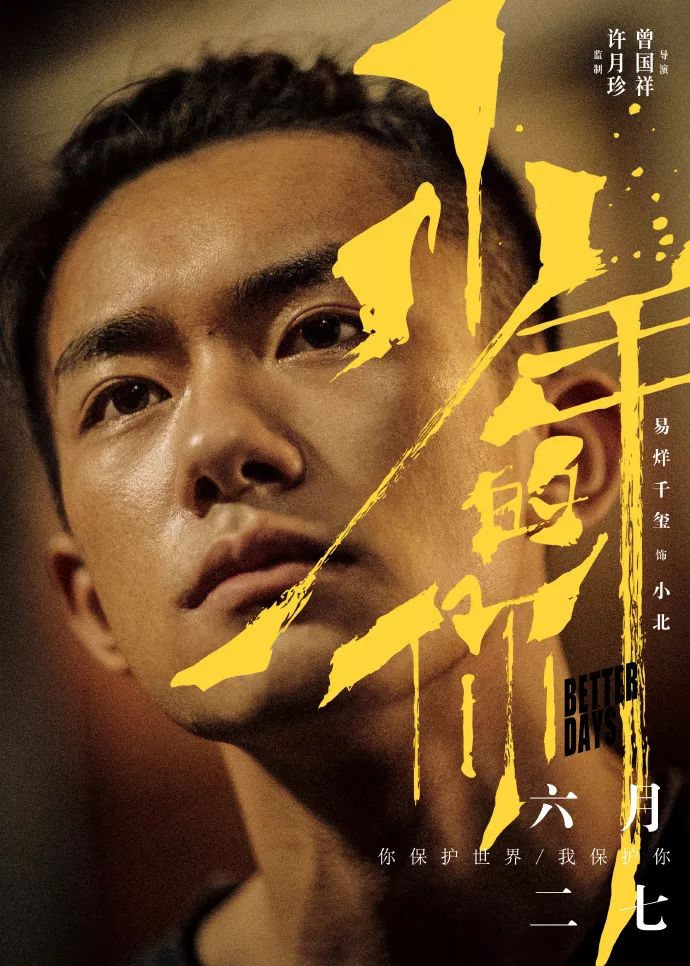
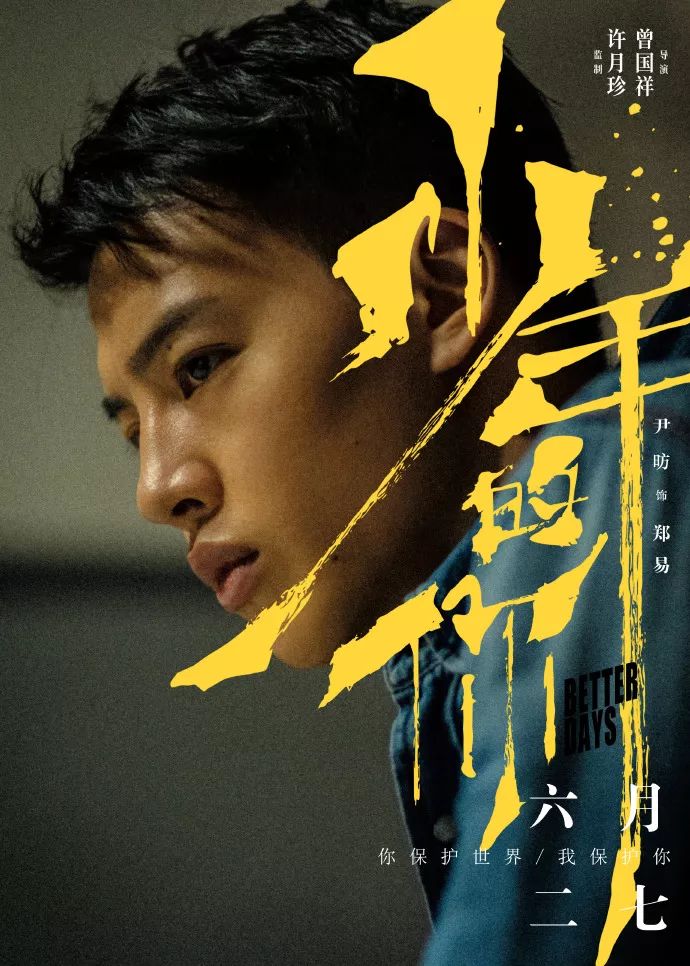
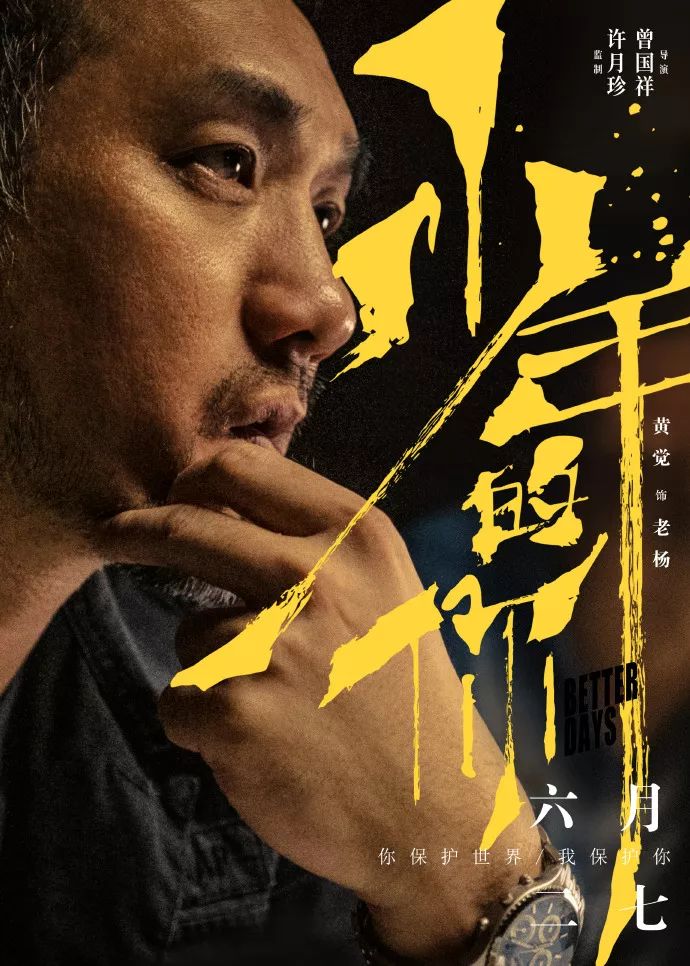
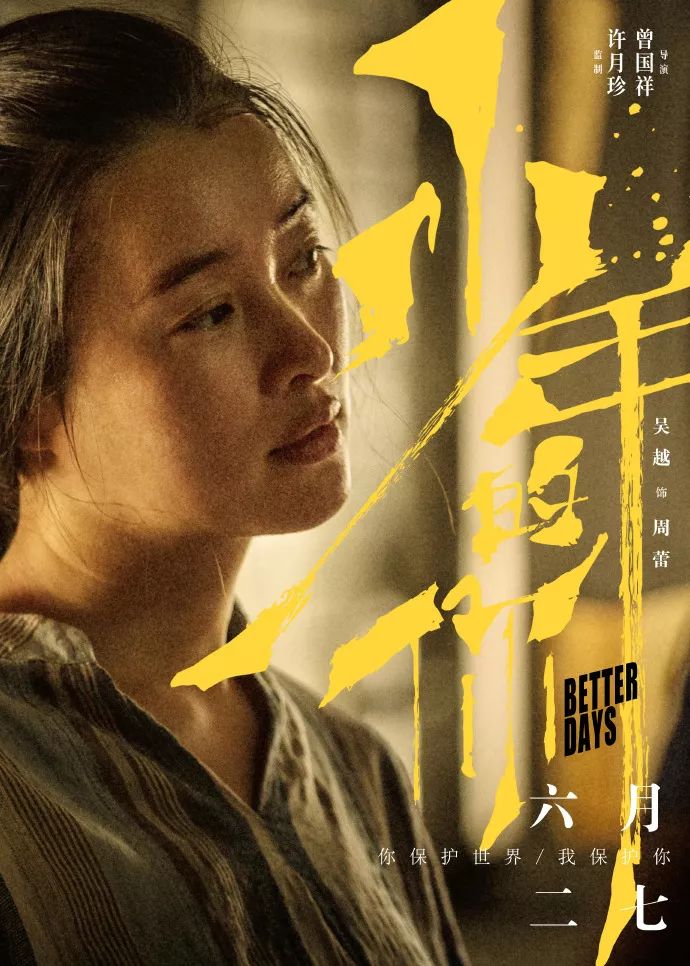
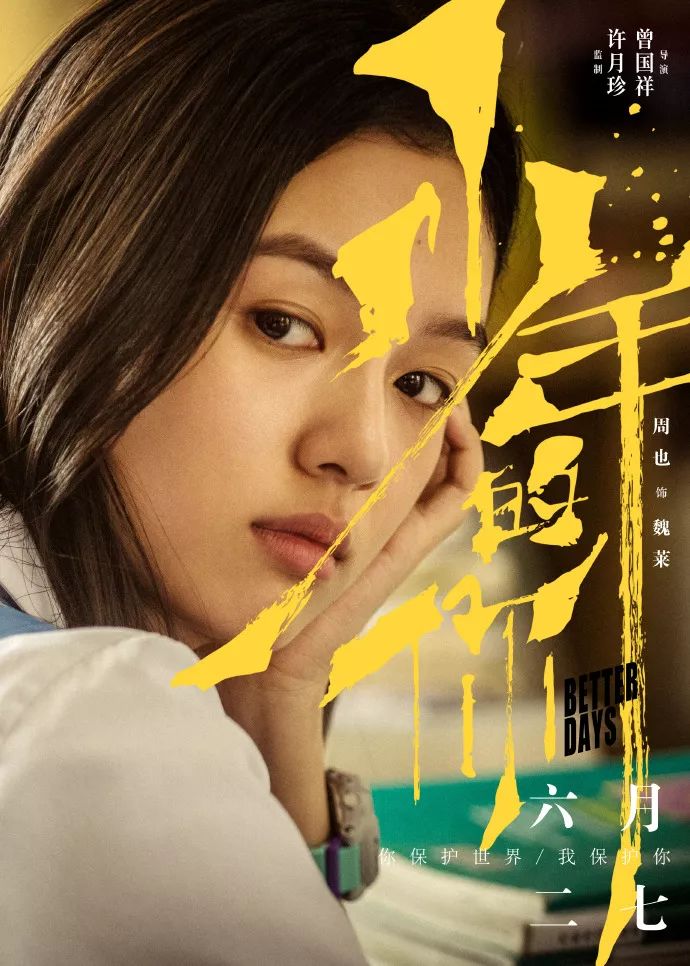
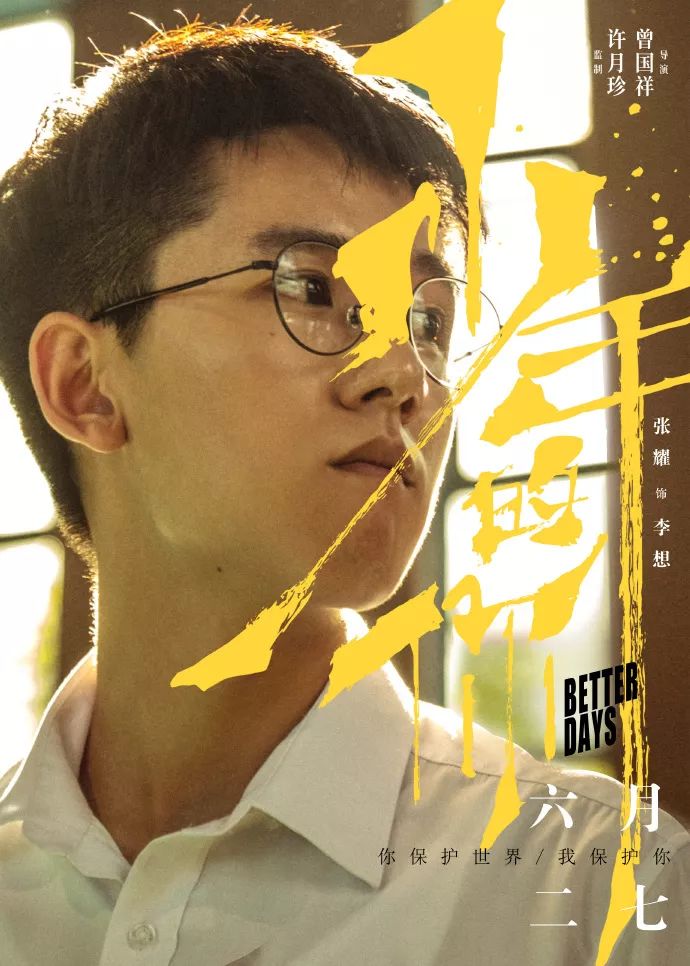
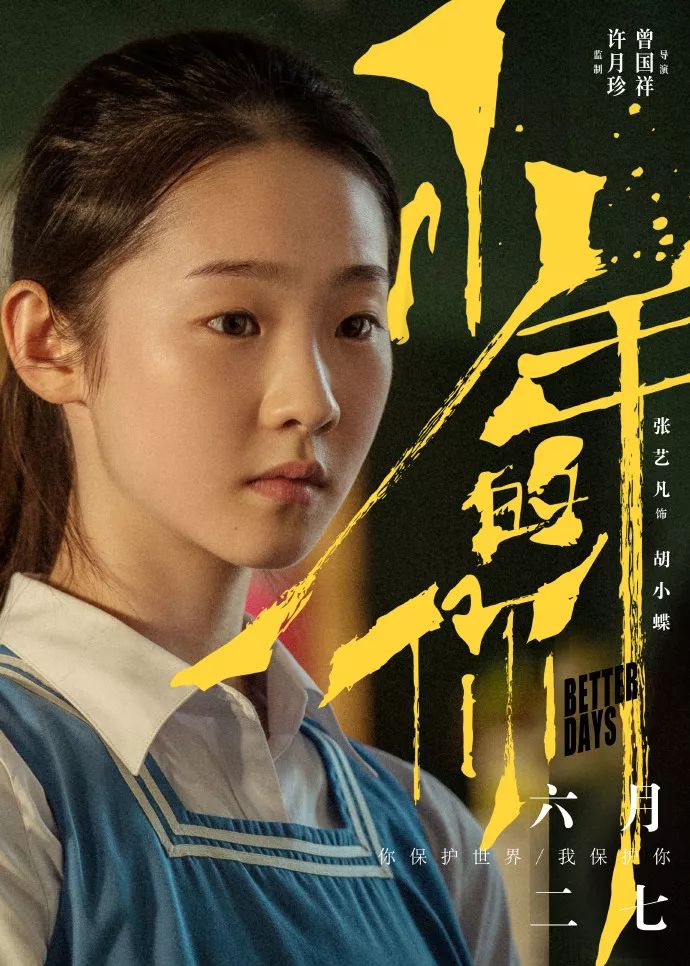
还有网友手绘的插画版海报
(图cr@_CHENxxxx_@11yeeee )
当然,除了海报设计非常有力
让人极具代入感之外
大大君我还是不想破坏这种氛围的
但是,易烊千玺的粉丝宣传文案
可以说真的是文案界的鬼才了
哈哈哈哈
今日份的沙雕快乐
请查收